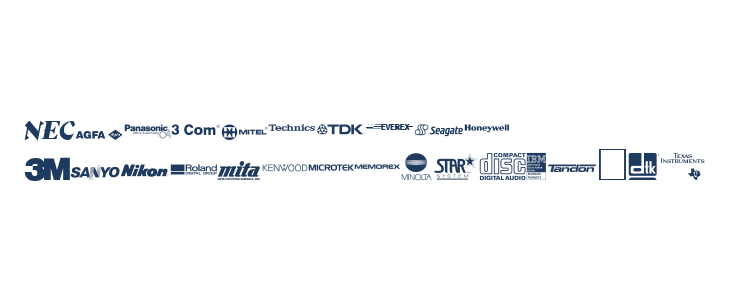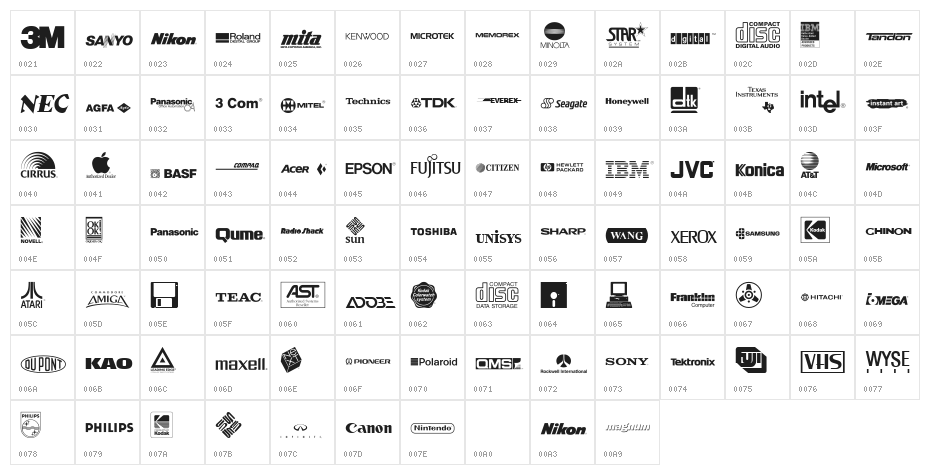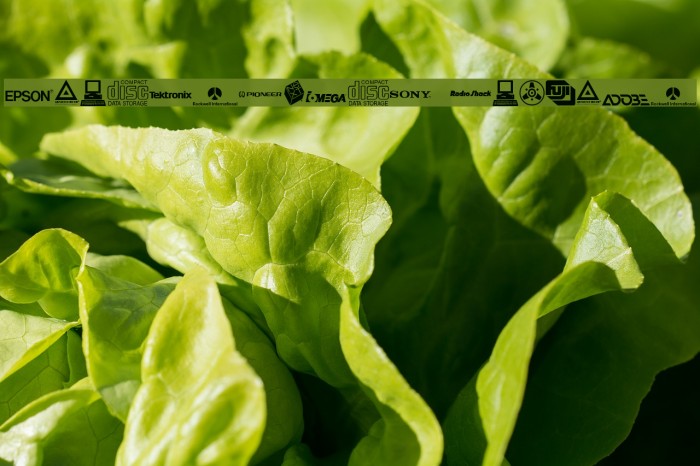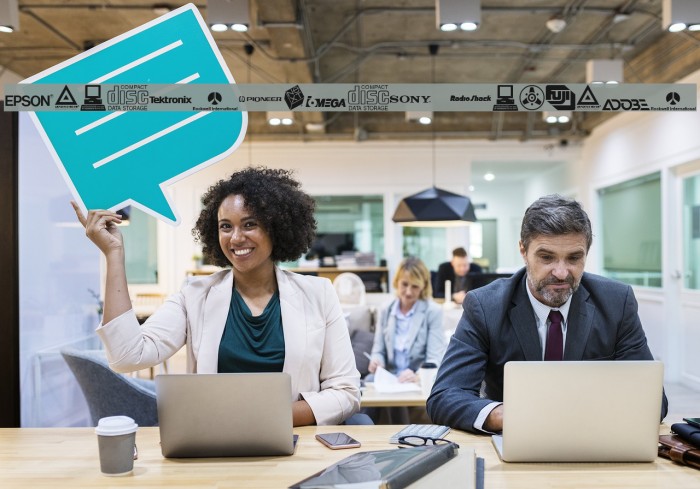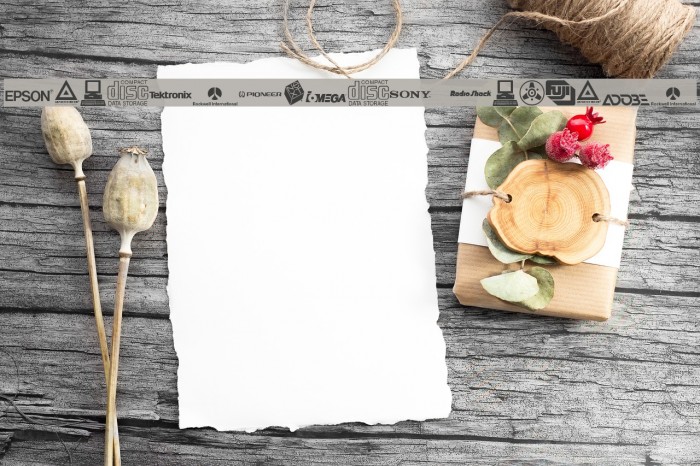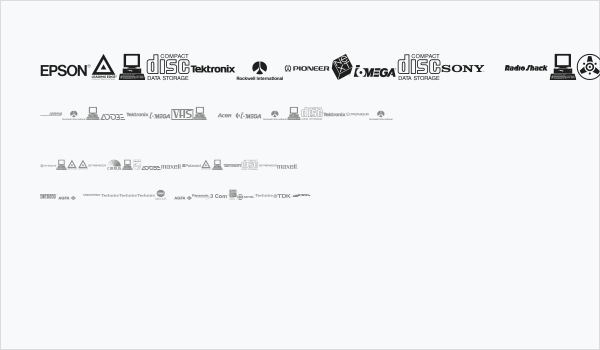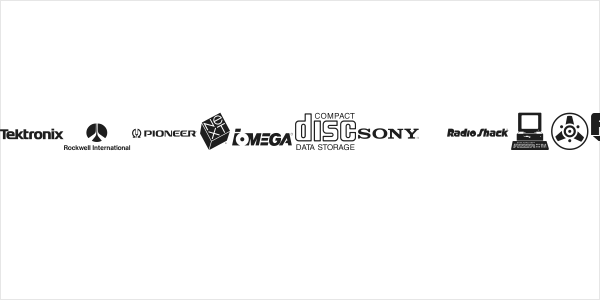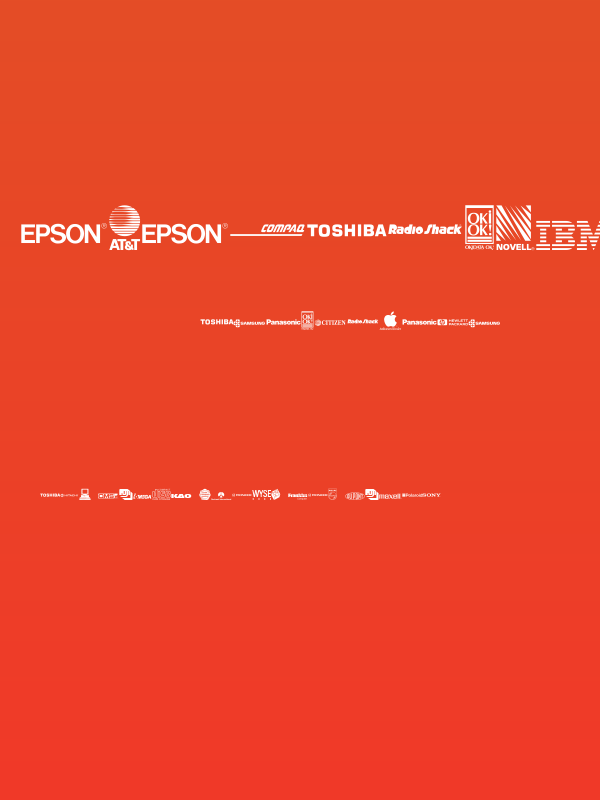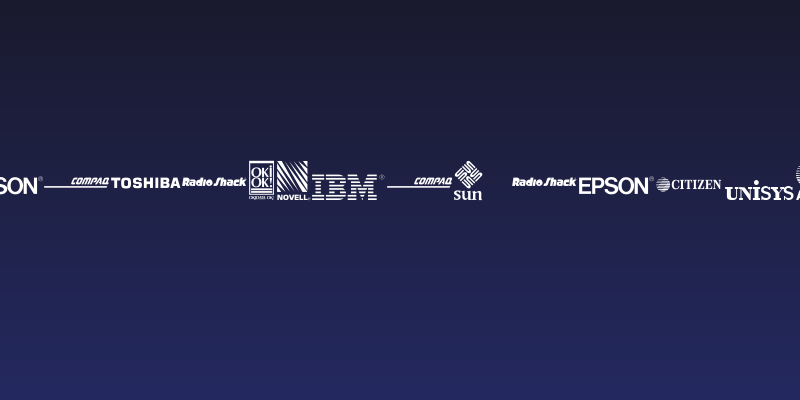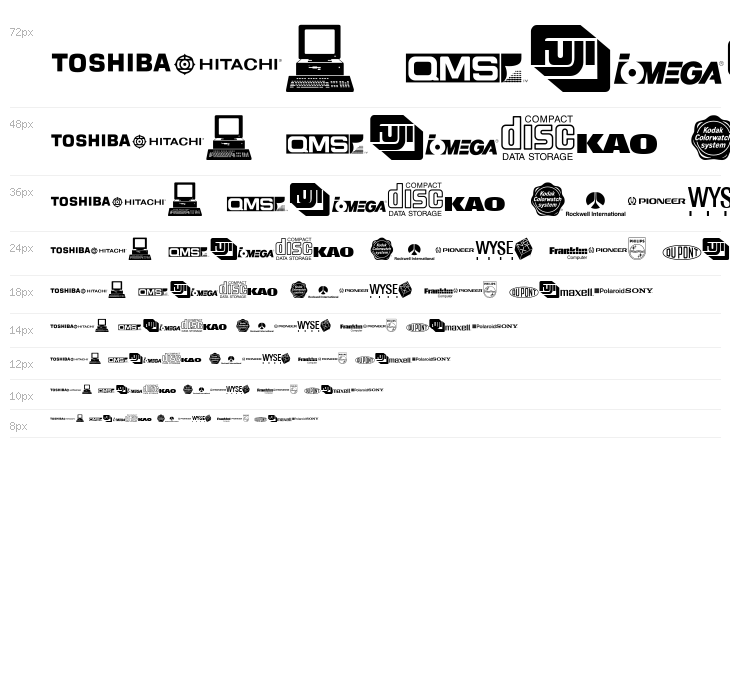
Electronics Regular Font
| Proyectos propuestos | This collection can be used for a study on branding and typography in the electronics industry, or as inspiration for logo design projects. |